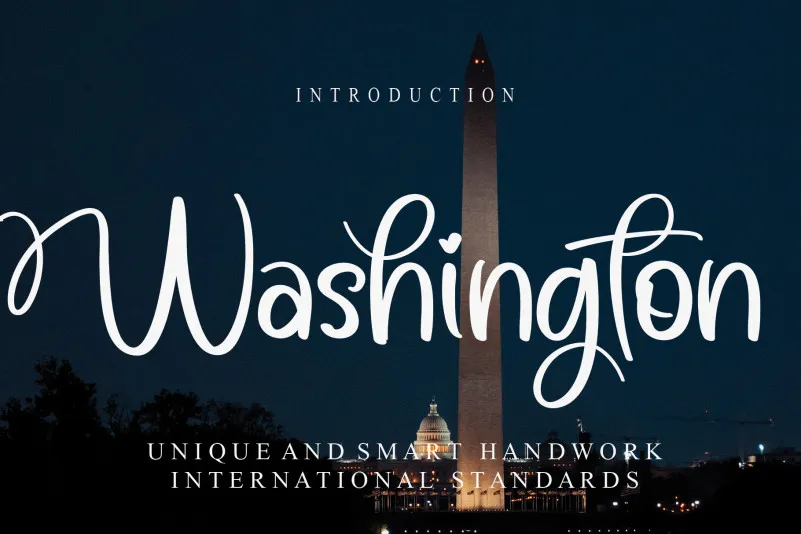
Washington Calligraphy Font – Download Grátis
Esta Washington Calligraphy Font é uma escolha perfeita para aqueles que procuram uma escrita elegante e romântica para seus projetos criativos. Com seu design sofisticado, essa fonte script oferece um toque delicado e envolvente a qualquer texto. Suas linhas fluidas e o brilho dos detalhes adicionados tornam cada letra única e cheia de personalidade, ideal para gráficos de newsletter, capas de livros ou até mesmo para adicionar um toque romântico em suas anotações pessoais. Escolhida cuidadosamente pela designer creativeletter, essa fonte não apenas adiciona sofisticação a seus designs, mas também garante uma experiência única e impressionante. Ela é perfeita tanto para os designers gráficos quanto para amantes da literatura que desejam dar um toque especial aos seus trabalhos. E com sua categoria de “Script Fonts”, essa font oferece a oportunidade de criar texturas fluidas e sutis, tornando-a uma escolha indelével para qualquer projeto em que você desejar adicionar personalidade e elegância à escrita.